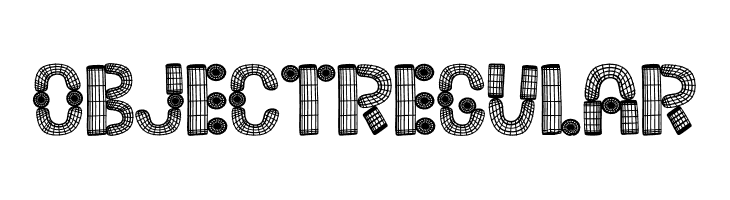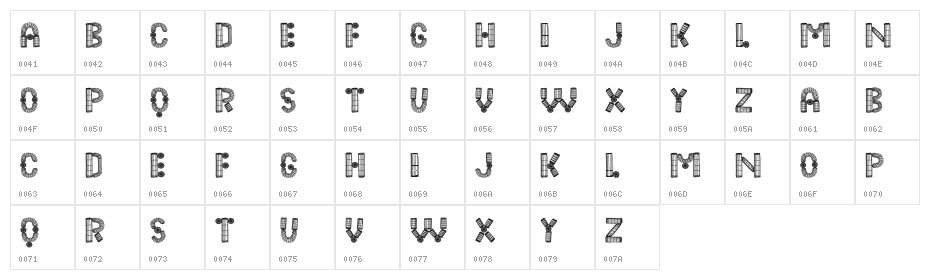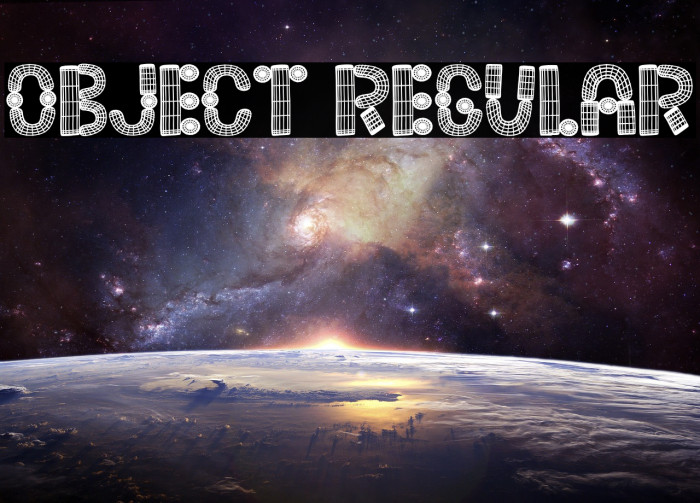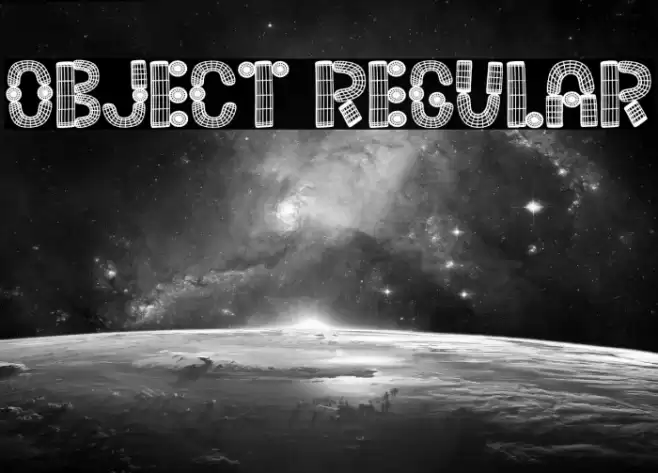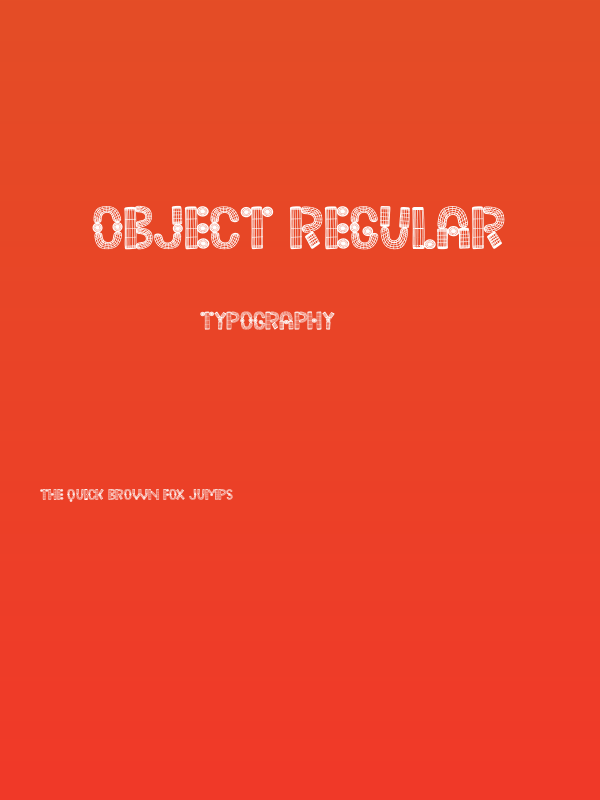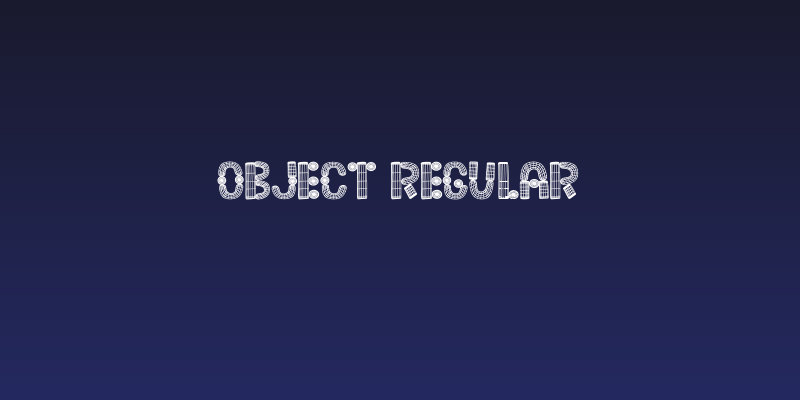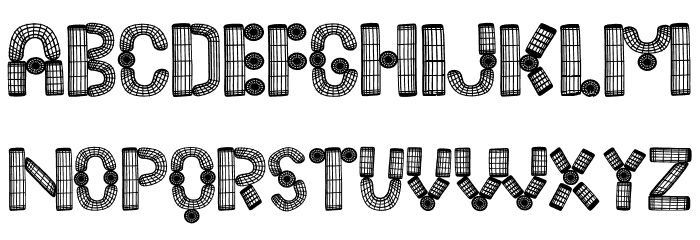
Object Regular Font
| Vorgeschlagene Projekte | Ideal for technology-themed posters, video game titles, sci-fi book covers, and branding for tech companies. |